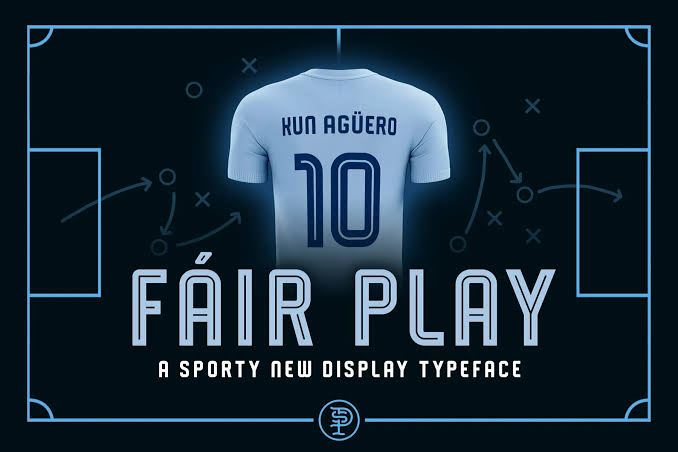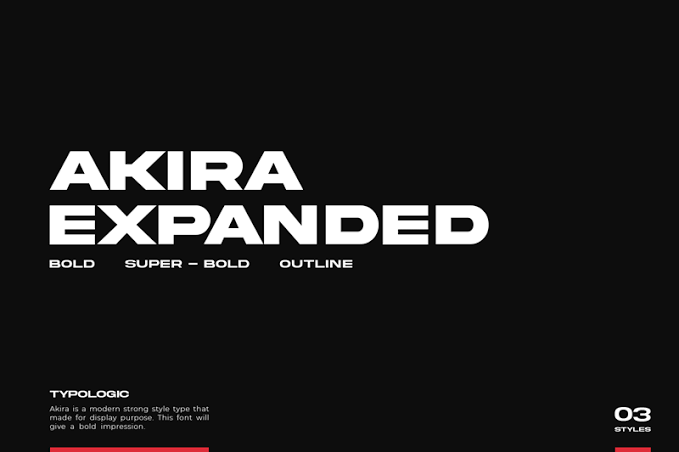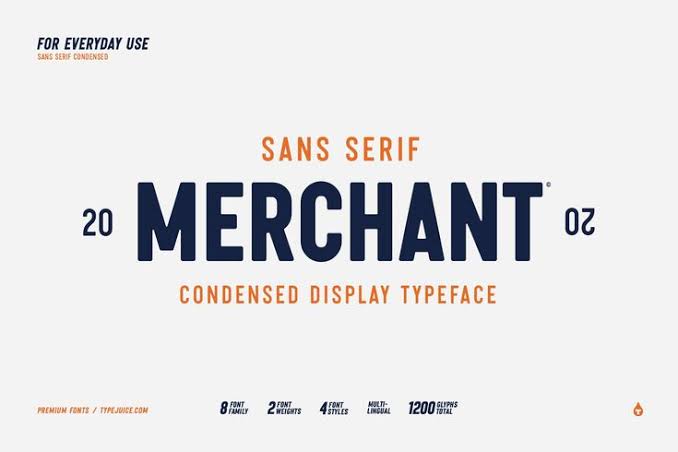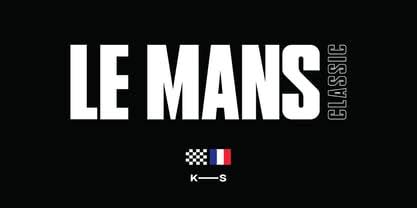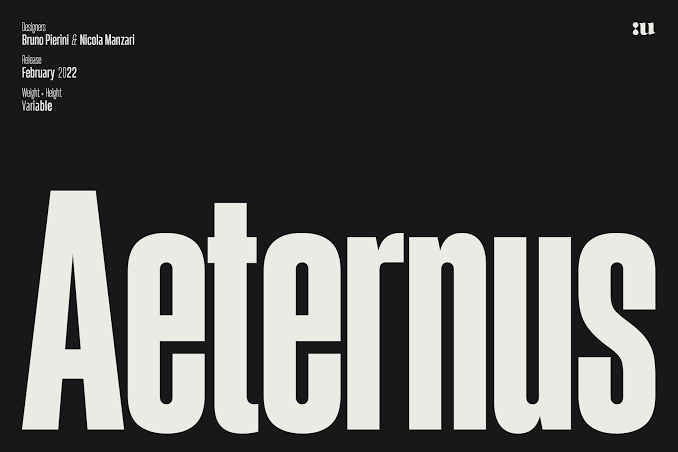
Desain grafis memang digunakan dalam berbagai bidang untuk menciptakan desain yang menarik untuk logo, fashion, packaging hingga website. Dalam bidang sport atau olahraga, desain grafis untuk logo dan lainnya memiliki beberapa karakteristik yang mencerminkan olahraga. Elemen desain seperti font yang digunakan untuk desain grafis bertema sport memiliki ciri dan karakteristik yang merepresentasikan sport.
Font yang digunakan dalam desain grafis bertema sport seringkali memiliki gaya huruf tebal, tajam, energik dan terlihat kuat. Tidak hanya font elemen seperti warna untuk desain sport sering menggunakan warna yang tajam dan solid seperti warna biru dan hitam. Elemen visual untuk desain sport dipilih untuk merepresentasikan kekuatan, ketangkasan dan semangat.
HAL YANG PERLU DIPERHATIKAN DALAM MENCIPTAKAN DESAIN SPORT
Desain grafis untuk kebutuhan sport biasanya terkait desain logo, desain atribut olahraga, poster gym dan acara olahraga. Grafis yang menarik dan sesuai dengan citra olahraga akan menciptakan tampilan visual yang menarik pecinta olahraga, perhatikan beberapa hal ini ketika ingin menciptakan desain grafis untuk sport1:
Warna yang Mengkomunikasikan Sport
Desain grafis untuk tema olahraga harus memilih warna yang bisa merepresentasikan olahraga. Biasanya sport identik dengan pesan kekuatan, energik, semangat dan kebugaran. Warna yang bisa merepresentasikan hal tersebut biasanya warna merah, oranye, biru, hijau dan hitam.
Banyak desain bertema sport yang menggunakan warna merah dan kuning atau biru dan hitam. Kombinasi warna biru dan oranye juga banyak ditemui dalam desain grafis bertema sport. Warna tersebut bisa digunakan dalam saturasi yang tinggi dan warna solid agar terlihat profesional.
Pastikan Elemen Merepresentasikan Identitas Brand
Untuk desain logo brand sport biasanya perlu memiliki elemen visual yang merepresentasikan sport. Brand sport umumnya akan memiliki tampilan logo yang terlihat tajam, kaku dan strong. Penggunaan tipografi tebal dan tajam menjadi ciri khas utama logo sport.
Pemilihan ikon gambar dan ilustrasi untuk brand sport juga memiliki tampilan yang terlihat tajam dan mencolok. Pilih elemen visual seperti font, ikon, ilustrasi dan gaya visual yang bisa merepresentasikan desain sport. Elemen-elemen visual ini berperan penting dalam mengkomunikasikan nilai dan karakter brand pada pelanggan.
Sesuaikan Style dengan Jenis Desain
Desain grafis tema sport dapat berupa logo, poster, fashion dan packaging, terkadang untuk kebutuhan event olahraga akan membutuhkan desain karakter. Gaya visual harus menarik dan merepresentasikan brand dengan baik. Logo untuk brand sport biasanya sering menggunakan jenis logo kombinasi atau logotype dan logo karakter.
Brand sport terkenal dunia seperti nike dan adidas memiliki gaya desain logo yang terlihat tajam dan mencolok. Bentuk logo yang sederhana akan mudah dibaca dan diingat oleh audiens. Logo karakter juga dapat merepresentasikan karakter erek dengan baik.
Sementara untuk desain poster, seringkali memiliki style minimalis dan modern agar mudah terbaca dan berkesan profesional. Sebagian besar desain grafis yang terkait dengan olahraga memiliki gaya minimalis yang bersih dan profesional. Pastikan juga style desain memiliki gaya visual yang konsisten dalam media cetak sehingga visualnya tetap sama.
Perhatikan Tren Desain Grafis Sport
Untuk menciptakan desain grafis bertema sport atau olahraga, perhatikan tren desain dalam bidang sport. Desain grafis dalam bidang sport memiliki tren yang menyesuaikan dengan tren desain dan perubahan preferensi konsumen. Tren desain modern seperti geometrik shapes, abstrak pattern, tipografi tebal, dan warna yang tajam.
Gaya visual desain modern menciptakan tampilan brand sport yang timeless, unik dan terlihat mencerminkan kekuatan. Pemilihan elemen visual juga harus menciptakan tampilan menarik dan harmonis. Tren desain sport seringkali mengutamakan memilih desain yang sederhana dan tajam untuk merepresentasikan kekuatan.
TIPOGRAFI UNTUK DESAIN SPORT
Untuk menciptakan desain grafis bertema olahraga, penting untuk memilih font yang bisa merepresentasikan identitas desain tema sport. Beberapa tipografi ini dapat digunakan untuk menciptakan desain visual tema port termasuk logo brand sport. Berikut beberapa rekomendasi font untuk desain bertema sport:
Grand Slam
Brand untuk olahraga tidak harus memiliki jenis font bersih yang tajam. Jenis font script yang tebal juga bisa digunakan untuk brand sport, seperti jenis font ini. Font grand slam ini memiliki tampilan huruf script yang termasuk jenis handwritten yang tebal.
Font script yang tebal ini dapat menciptakan tampilan desain grafis bertema sport yang menonjol. Jenis fontnya dapat merepresentasikan kesan brand yang energik dan semangat. Bentuk huruf dengan sudut melengkung yang ramah membuatnya cocok untuk poster event olahraga atau promosi brand sport.